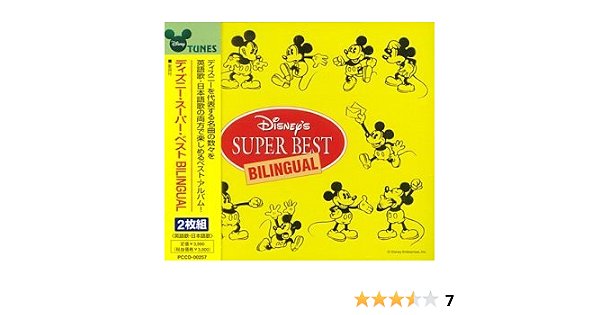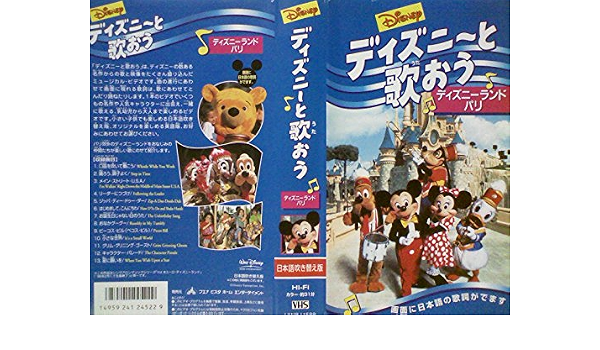
ディズニー フォント 無料 日本語. ディズニーフォントを調べるときは、英語にしてくださいね。 カタカナで検索すると、ディズニーフォントが出てこないため注意。 その2ためしがき(日本語) 日本語でディズニーフォントを検索できる「ためしがき」。. ウォルト・ディズニー風フォント 商用可有料レベルの無料素材が10日ごとに10枚増え続けているサイト「un Old 1669 「スマホで読書」を効率的に!Kindleアプリの超便利な使い方 Old. 画像の加工や diy でペーパーアイテムを作る時に何かと使える 無料 フォントを集めました。 ウェディングアイテムにも人気の ディズニー フォントや年賀状に使える日本語の フリーフォント など盛りだくさんですよ! 専門業者に頼むと高額な料金が掛かってしまう事が多いペーパーアイテ.
Mickey in Fancy > Cartoon 3,054,177 downloads (499 yesterday) 25 comments 2 font files. ディズニー映画のプリンセスの中でも人気の高いラプンツェル! そんな「塔の上のラプンツェル」のフォントを発見したので、ご紹介します! さらに、フリーでダウンロードすることができます。 しかし、利用規約などは各々で確認してください. ためしがき 日本語のフリーフォントを検索できるサイト ためしたい言葉・文章を入れてください 入力するとフリーフォントが試せます ためしがき Mgen 縦書き つぶやく シェア 送る.
ディズニーフォントもパソコンがないと使えな。使える! iPhoneにインストールして写真に文字を入れるアプリ「Phonto」を使えばダウンロードからインストール、文字入れまで iPhone で全部できる! ディズニーフォントのダウンロードからインストールまでを解説します。. ウォルト・ディズニーのロゴのレタリングは、Waltographという名前のフォントによく似ています。 これは、Justin Callaghanがデザインした無料で個人使用できる書体です。 Waltographには、2つの種類があります 大文字、小文字、いくつかの合字や異体字がある通常のフォント、Waltograph 42と、小さいサイズやコンピューターの画面での読みやすさを高めることを目的としたユニケースの. 今回はディズニー映画のタイトルで使われている『ディズニーフォント素材』を紹介していきます。 *紹介しているフォントは全て無料です^^ ぜひお気に入りのフォントを見つけてデザインに生かしましょう٩ ( ‘ω’ )و *Mac(Macintosh)へフォントを追加.